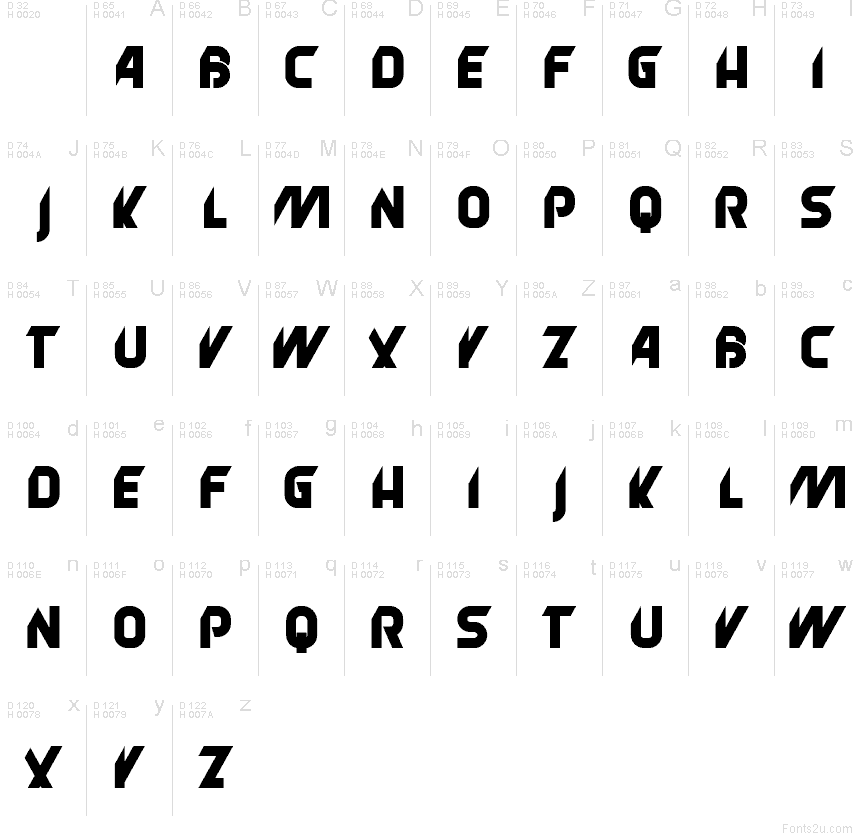
Translator Cola od Vladimira Nikolica je bezplatné techno písmo typu display s futuristickým a ostro rezaným charakterom. Písmená sú poskladané z masívnych geometrických blokov, ktoré sú prerezané ostrými diagonálnymi rezmi. Tie udržiavajú tvary v pohybe, od špicatej litery A až po stupňovité spoje a skosené rohy celého súboru.
Skvele sa hodí na branding v oblasti hier a e-športov, plagáty v štýle sci-fi, obaly hudobných albumov, titulné karty či grafiku pre technologické podujatia, kde pomáha odovzdať odkaz svojím strohým, mechanicky vytvoreným dojmom. Ako bezplatný font je vhodný aj na krátke nadpisy, logá a vizuály rozhraní, pretože tieto orezané uhly dodávajú aj krátkym slovám napätý, inžiniersky rytmus.